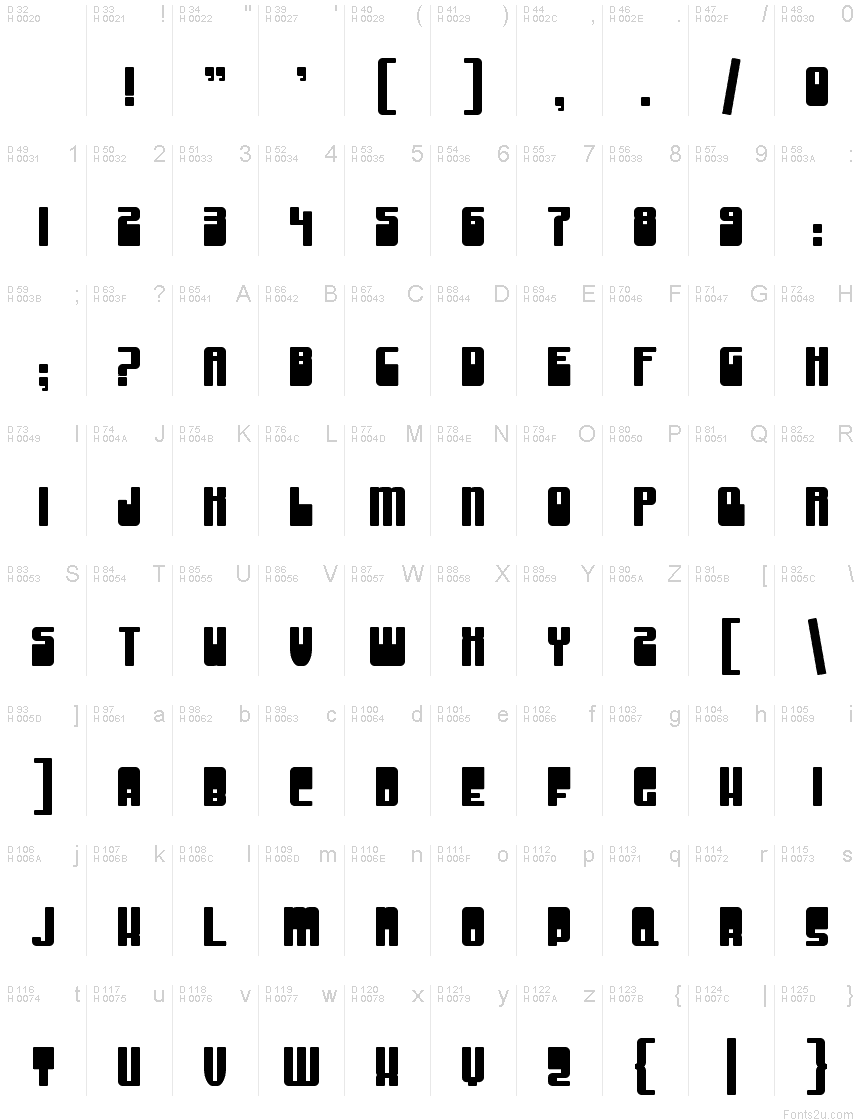
Groove Machine Upright Bold
Groove Machine Upright Bold od Shywedge to darmowy, groovowy krój pisma typu display. Ciężkie pionowe kreski, zaokrąglone rogi i ciasno upakowane kształty nadają mu pulsującej klubowej energii, przywodząc na myśl stosy głośników lub equalizer zatrzymany w połowie beatu. Rodzina Groove Machine Upright stawia na wysokie i skondensowane formy, dzięki czemu Twoje teksty brzmią głośno, wyraziście i są gotowe porwać tłum.
Użyj Groove Machine Upright Bold do stworzenia wyróżniających się nagłówków na plakatach muzycznych, klubowych ulotkach, logotypach DJ-skich, oprawie festiwali, tytułach gier retro czy odważnych grafikach na merch. Ten darmowy font świetnie sprawdza się w dużych, kontrastowych layoutach, gdzie słowa muszą krzyczeć. W mniejszych rozmiarach połącz go z czystym, geometrycznym krojem bezszeryfowym, aby zachować czytelność, podczas gdy masywne kształty zajmą się głównym uderzeniem.